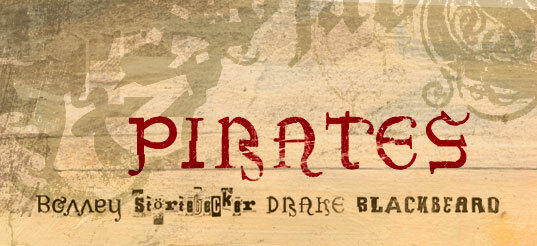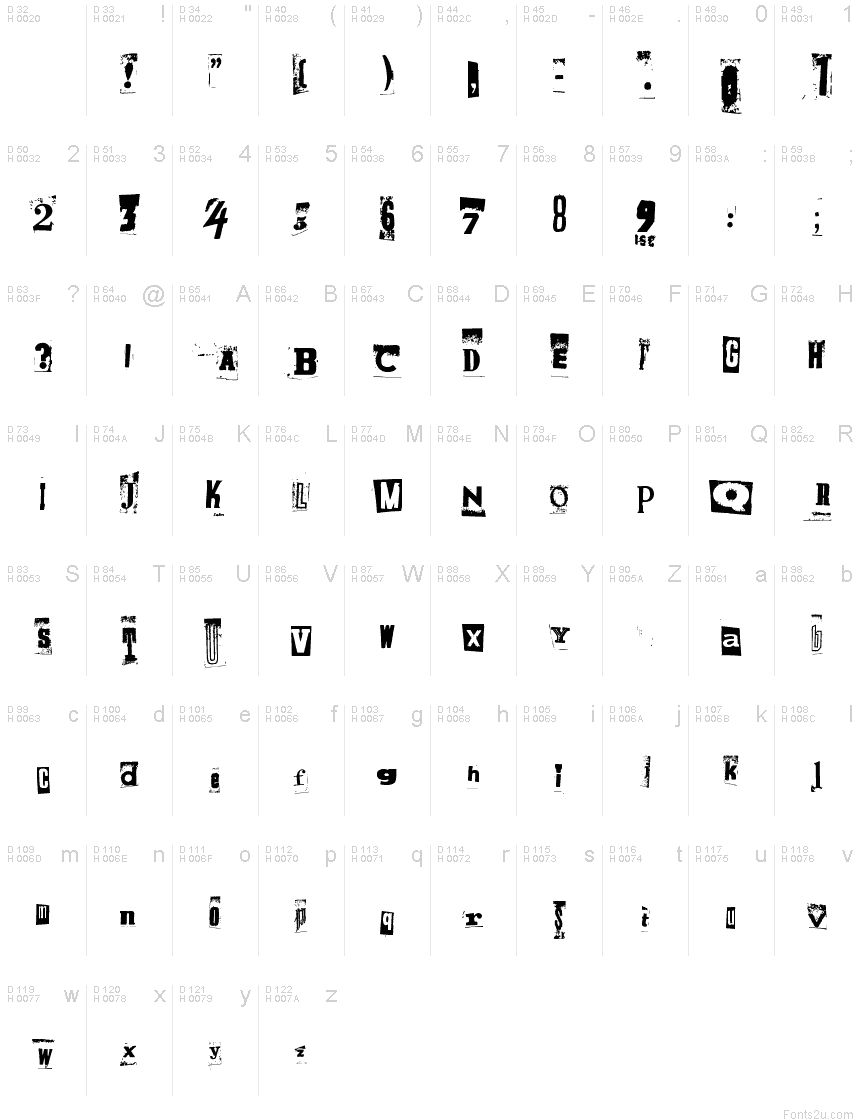
PiratesStoertebecker
Pirates Stoertebecker, autorstwa Felixa Bradena z Floodfonts, to darmowy krój displayowy w stylu wycinanki, z "pirackim", surowym i podniszczonym charakterem. Litery wyglądają jak zdjęte ze starych afiszy lub karczemnych ogłoszeń – łączą w sobie toporne, atramentowe formy, krzywe bloki, poszarpane krawędzie i nierówną grubość, dzięki czemu cały napis sprawia wrażenie buntu i kolażu, a nie uporządkowanego tekstu.
Idealnie sprawdzi się na tytułach plakatów, okładkach książek, ulotkach festiwalowych, w brandingu gier i menu pubów, gdzie potrzeba morskiego, surowego klimatu. Jako darmowy font, najlepiej wypada w krótkich nagłówkach, etykietach i tytułach, ponieważ jego poszarpany rytm i posklejany charakter oddają klimat szybciej niż jakikolwiek bardziej uładzony font dekoracyjny.